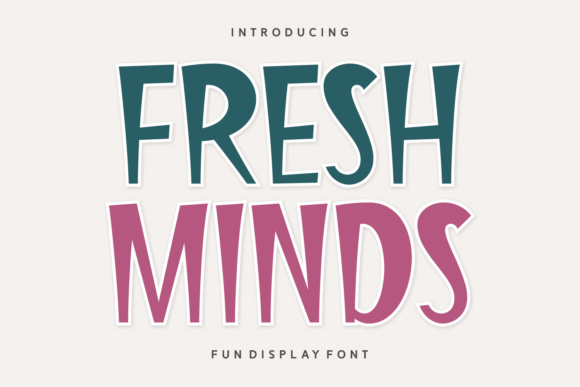
Fresh Minds
Fresh Minds – A Fonte que Transforma Ideias em Arte
Se você busca uma tipografia que una criatividade e versatilidade, Fresh Minds chegou para mudar o jogo. Desenvolvida com um toque cartoon e ao mesmo tempo limpa, ela se adapta perfeitamente a projetos de t‑shirts, stickers, tumbler, sublimação, citações, e muito mais.
- Design ousado para capas de livros – Traça linhas marcantes que chamam a atenção nas prateleiras.
- Logotipos impactantes – Ideal para marcas que desejam transmitir personalidade e energia.
- Fonte infantil e baby – O estilo lúdico faz dela a escolha número 1 para projetos infantis, como convites de aniversário e material escolar.
- Aplicação em artesanato e DIY – Perfeita para criadores de stickers, decals e itens personalizados.
- Legibilidade em headlines – Apesar do visual elaborado, mantém clareza suficiente para títulos e textos de destaque.
- Facilidade para professores – Torna aulas e materiais didáticos mais atraentes, estimulando a atenção dos alunos.
Com Fresh Minds, cada detalhe conta. A fonte combina estética fantasiosa com funcionalidade prática, permitindo que designers – sejam eles iniciantes ou veteranos – elevem o nível de seus projetos sem esforço. Experimente hoje mesmo e descubra como ela pode potencializar sua criatividade em qualquer aplicação.